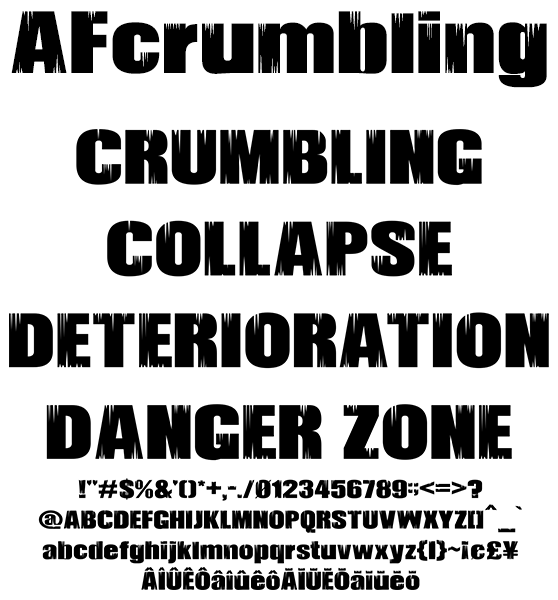
クラック欧文フォント AFcrumbling
AFcrumbling
輪郭に亀裂を施しました。凍結や劣化による亀裂をイメージしました。寒さ、崩壊、劣化を想像させるキーワードにご利用ください。記号類、マクロンやサーカムフレックスなどのダイアクリティカルマーク、訓令式やヘボン式で扱うÔやŌを収録、人名地名でもお使い頂けます。